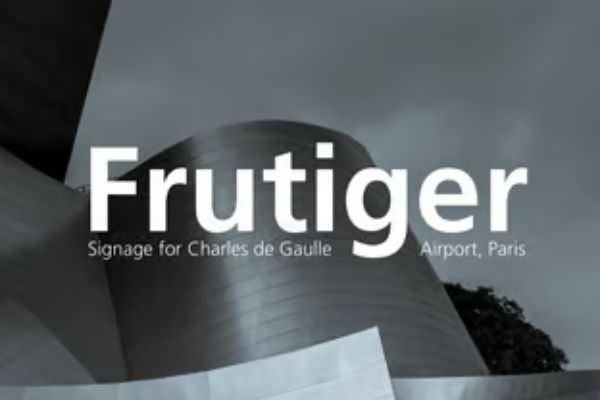
Frutiger® Pro 87 Extra Black Condensed
Frutiger 最初是为巴黎新戴高乐机场而开发,符合机场标牌的特定易读性要求。其字形的设计使得每个单独的字符都能快速、轻松地识别,因此非常适合标牌和展示。而 Frutiger 整个家族又有温暖精细的感受,近年来也在杂志和小册子上较小尺寸的正文中流行起来。Frutiger 还用于英国皇家海军、Telefónica O2、DHL 和 Raytheon 等品牌 logo。